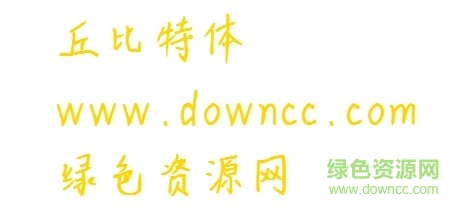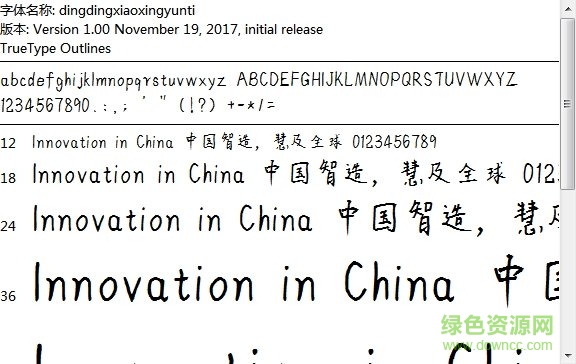
漢儀丘比特體
丘比特體是漢儀字庫(kù)在手機(jī)qq上推出的一款卡通字體,字跡端正清秀,中文清爽英文規(guī)整,是一款不錯(cuò)的手寫(xiě)字體,造型獨(dú)特自然呈現(xiàn),綠色資源網(wǎng)獨(dú)家推薦!
漢儀丘比特體字體介紹
丘比特體,也叫丁丁小幸運(yùn)體,沒(méi)有多余的圖形圖示,是一款好用的手寫(xiě)字體,讓人眼目一新,文字排版、海報(bào)廣告設(shè)計(jì)、藝術(shù)設(shè)計(jì)等方面都可以使用!